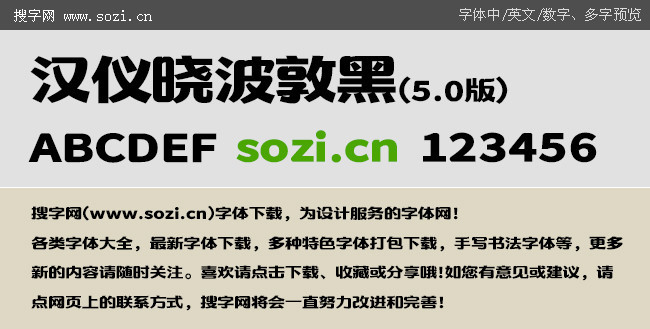
漢儀曉波敦黑5.0
搜字網(wǎng)提供一款漢儀曉波敦黑5.0字體下載,漢儀曉波敦黑是一款漂亮的藝術(shù)黑體字體。由漢儀曉波工作室出品,漢儀曉波敦黑是一款基于常規(guī)黑體之上創(chuàng)作的標(biāo)題字,它汲取了黑體嚴(yán)肅而精確的特征,又不失手寫的溫潤感,5:4的長寬比例使字體更顯穩(wěn)重,能適用于各類標(biāo)題字,企業(yè)標(biāo)準(zhǔn)字的應(yīng)用。(本字體為個人非商用版,如需要商用請聯(lián)系漢儀公司購買版權(quán))